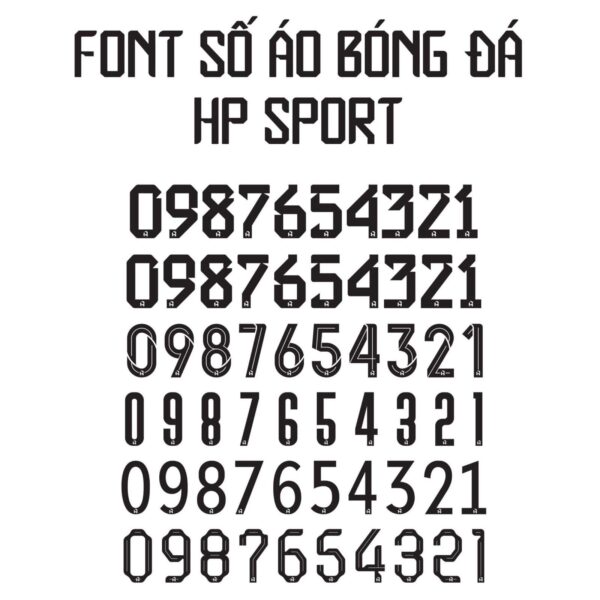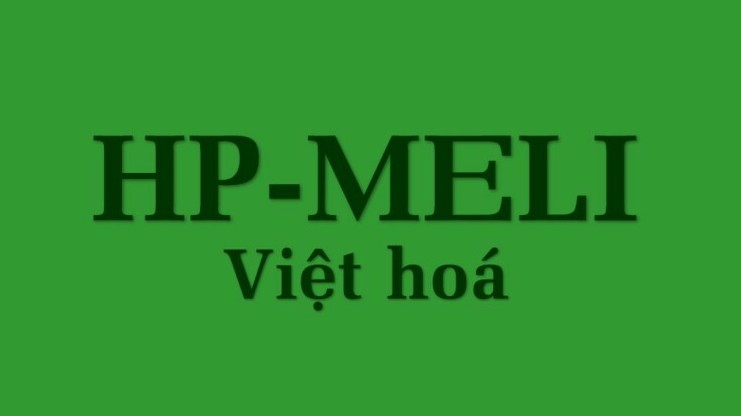
Tải 20+ bộ font HP Việt hóa: Phông chữ chuẩn cho giáo dục và thiết kế nghệ thuật
Hệ thống font HP là một trong những bộ phông chữ quen thuộc và không thể thiếu đối với cộng đồng làm nghề thiết kế, giáo dục tại Việt Nam. Với ưu điểm là sự đa dạng từ các dòng phông chữ tập viết lớp 1 đến các kiểu chữ nghệ thuật bay bổng, việc sở hữu font HP Việt hóa giúp người dùng trình bày nội dung tiếng Việt một cách chuẩn mực và thẩm mỹ.
Khám phá các đặc trưng thẩm mỹ của hệ thống font HP Việt hóa
Điểm lôi cuốn đặc trưng của dòng phông này chính là sự tỉ mỉ trong việc mô phỏng các đường nét thủ công truyền thống. Các mẫu bộ font HP Việt hóa thường sở hữu cấu trúc ký tự thanh thoát, giúp văn bản toát lên vẻ gần gũi nhưng vẫn rất chuyên nghiệp. Phiên bản Việt hóa đã được xử lý bảng mã Unicode chuẩn, đảm bảo các dấu hỏi, ngã, nặng được đặt ở vị trí cân đối, duy trì nhịp điệu của bộ chữ gốc mà không gặp rủi ro về lỗi hiển thị ký tự trên các hệ điều hành phổ biến.
Sự ổn định của hệ thống phông HP còn thể hiện ở tính đa năng. Dù bạn cần phông chữ có ô ly chuẩn giáo dục hay các kiểu phông script trang trí, font HP Việt hóa luôn mang lại khả năng hiển thị sắc sảo. Đây là phương án hiệu quả để định hình phong cách cho những dự án kiến trúc trường học, khu vui chơi trẻ em hay các không gian nghỉ dưỡng mang hơi hướng truyền thống, giúp thông điệp của bạn dễ dàng chạm đến cảm xúc của người xem.
Bộ font Hp Việt hóa chuẩn 01
Để hỗ trợ bạn trong việc lựa chọn và ứng dụng hiệu quả vào công việc sáng tạo, dưới đây là bảng thông số chi tiết của hệ thống phông chữ HP đã được kiểm tra tính ổn định.
Thông số tài nguyên Chi tiết nội dung
Phân loại phong cách Calligraphy / Script / Educational
Bảng mã hỗ trợ Unicode Việt Nam chuẩn
Nhóm phông tiêu biểu HP001 (Ô ly), HP Script, HP Decorative
Mục đích phù hợp Soạn giáo án, Logo, Bảng hiệu, Decor nội thất
Tư vấn lựa chọn: Khi thực hiện download font hp full, bạn nên chú ý phối hợp kiểu chữ đứng cho nội dung thuyết minh và dùng kiểu viết tay (Script) cho các tiêu đề hoặc câu slogan. Sự kết hợp này giúp bản thiết kế của bạn có chiều sâu thị giác và tăng khả năng nhận diện thông tin quan trọng.
03 Ứng dụng đưa phông chữ HP vào thực tế trình bày hồ sơ kiến trúc
Nhờ diện mạo giàu tính thực tiễn và tính nghệ thuật cao, việc sử dụng các mẫu từ bộ download font hp Việt hóa mang lại giá trị lớn trong khâu trang trí và quảng bá công trình:
• Hệ thống nhận diện cho không gian giáo dục: Sử dụng các dòng phông HP001 cho bảng tên lớp, biển chỉ dẫn tại các trường mầm non hoặc tiểu học lắp ghép giúp không gian trở nên thân thiện và đồng bộ với môi trường sư phạm.
• Trang trí không gian nội thất Zen: Những nét chữ viết tay từ hệ thống HP rất ăn ý khi xuất hiện trên chất liệu gỗ khắc laser hoặc in tranh decor. Phông chữ này giúp phòng khách nhà lắp ghép toát lên vẻ thư thái và chiều sâu văn hóa.
• Thiết kế bộ quà tặng thương hiệu: Bạn có thể dùng font HP nghệ thuật trên các nhãn dán sản phẩm hoặc thiệp cảm ơn, tạo ấn tượng về sự tỉ mỉ và trân trọng giá trị truyền thống đối với khách hàng và đối tác.
Bộ font Hp Việt hóa chuẩn 02
03 Lưu ý kỹ thuật để khai thác tối đa bộ font HP Việt hóa
Để khai thác hiệu quả vẻ đẹp của dòng phông đa năng này mà không làm rối mắt người xem, người thiết kế nên lưu tâm một số kinh nghiệm kỹ thuật sau:
• Kiểm soát kích thước khi in ấn: Đối với các phông chữ có ô ly giáo dục, bạn nên thiết lập kích thước chữ ở mức trung bình (khoảng 14-18pt) để các đường kẻ hiển thị rõ ràng, không bị nhòe nét khi in ra hồ sơ dự án.
• Nới rộng khoảng cách dòng: Do cấu trúc chữ viết tay thường có các nét móc vươn dài, bạn nên để khoảng cách dòng thoáng hơn một chút để các ký tự không bị chồng lấn, giữ được sự minh bạch cho văn bản.
• Lựa chọn nền màu phù hợp: Phông chữ nghệ thuật HP phát huy hiệu quả thị giác cao khi đặt trên các nền màu đơn sắc hoặc nền vật liệu tự nhiên, giúp các đường nét uyển chuyển của bộ chữ được tôn vinh rõ ràng.
Bộ font Hp Việt hóa chuẩn 03